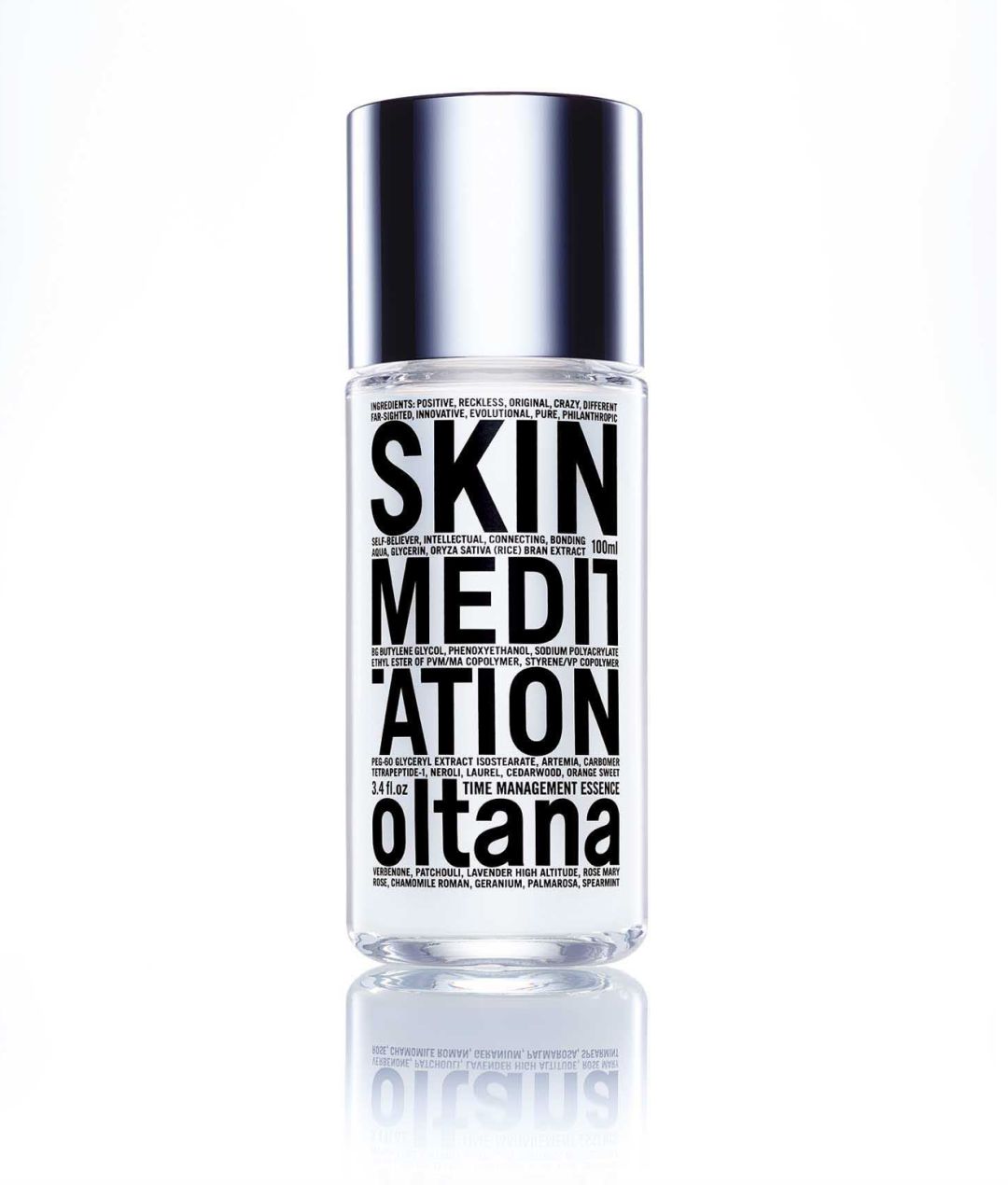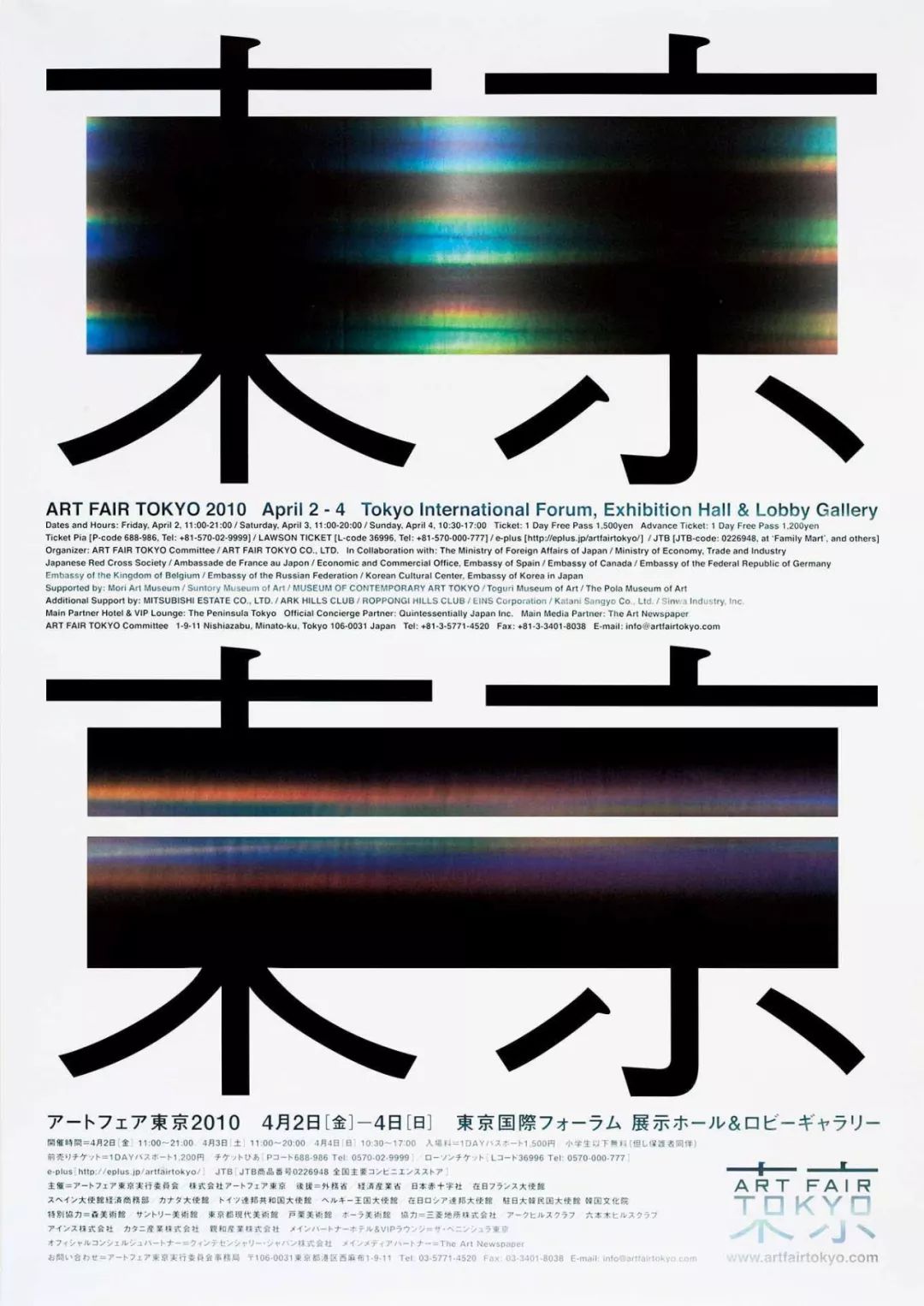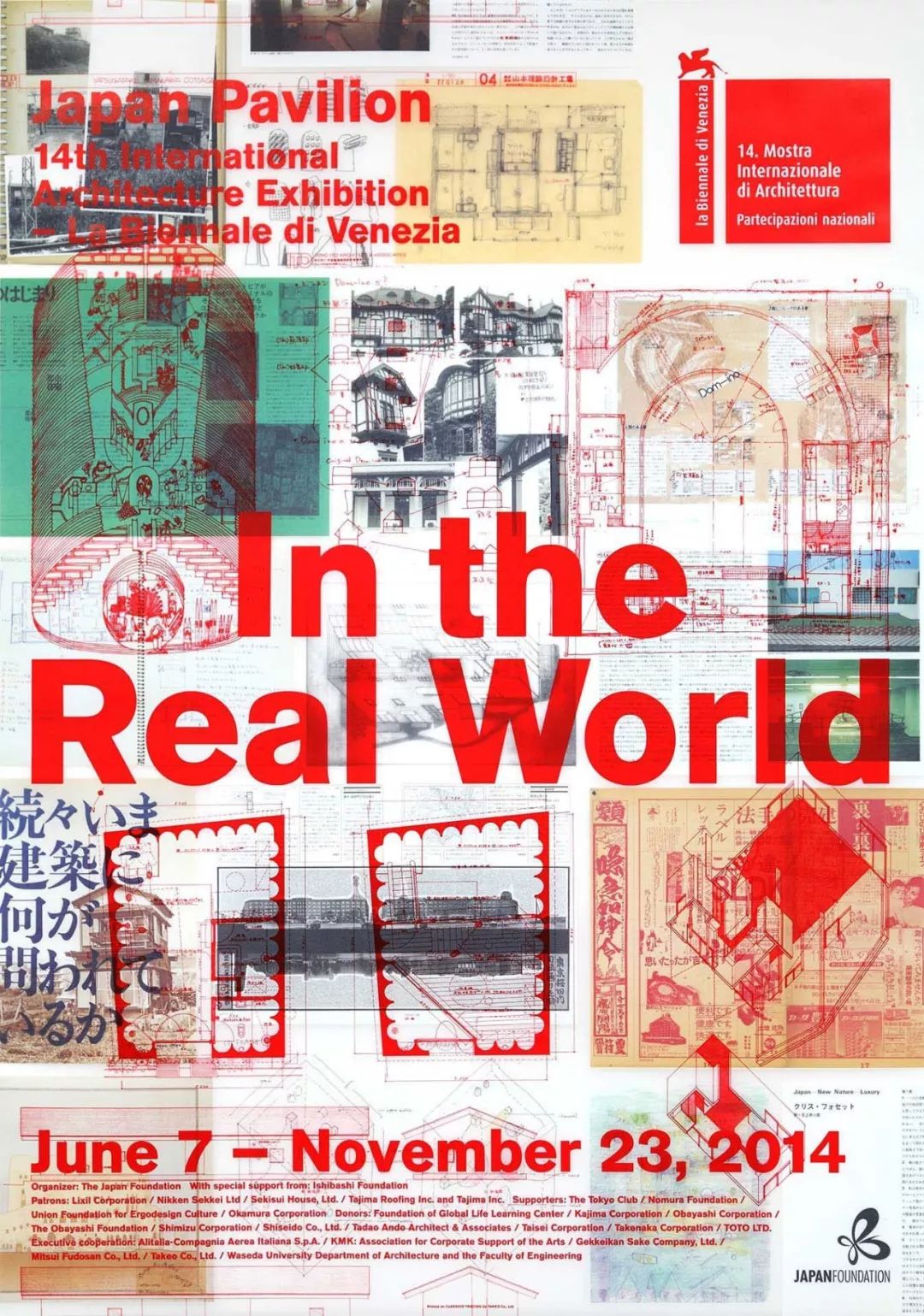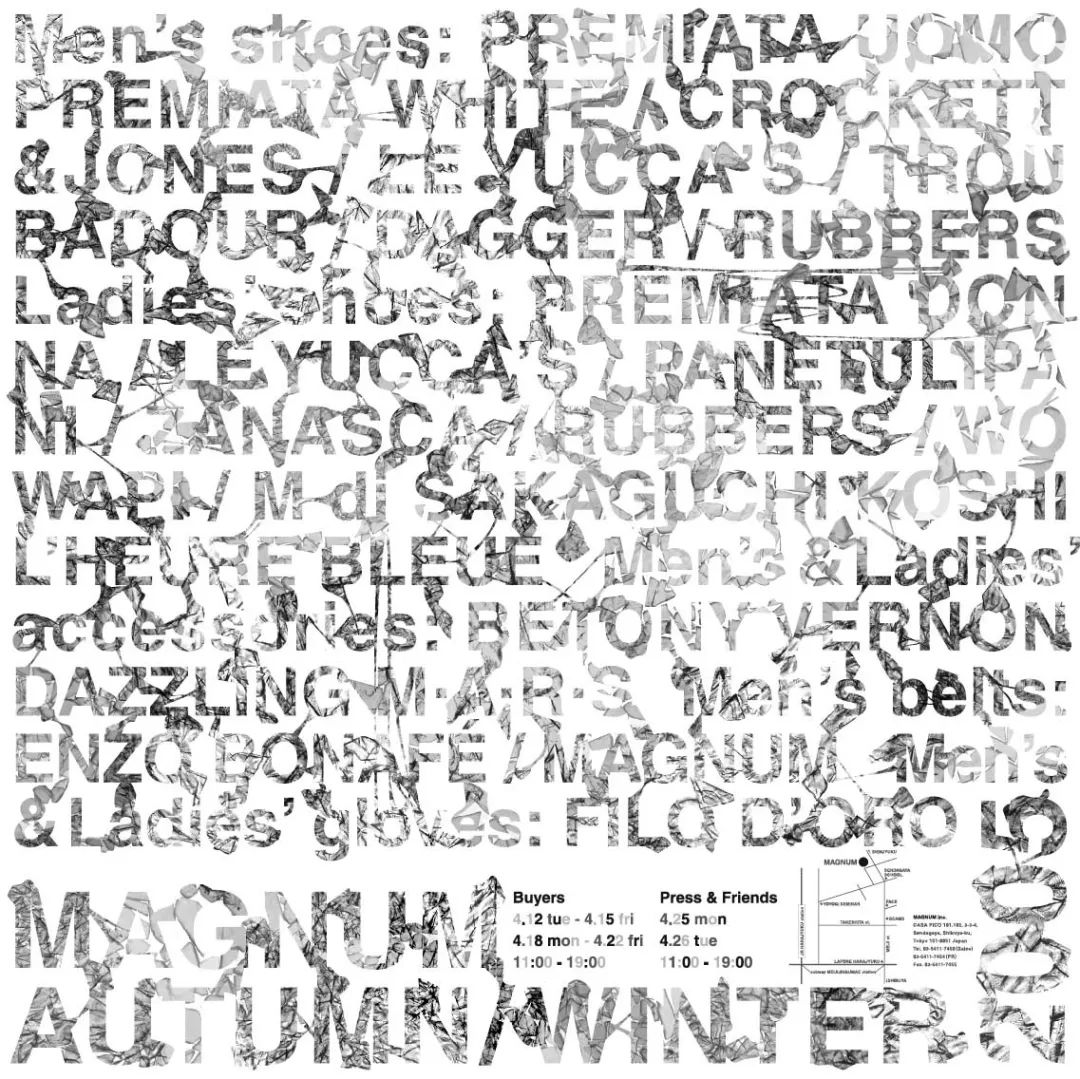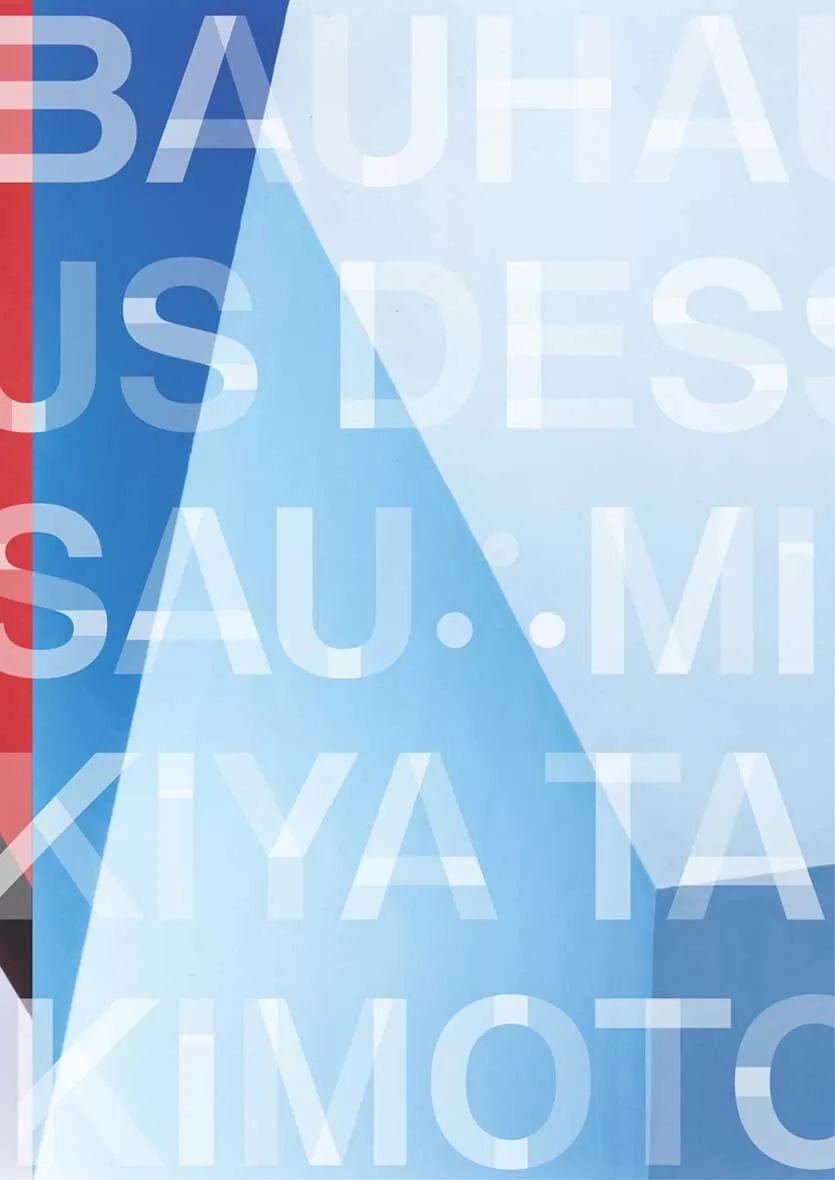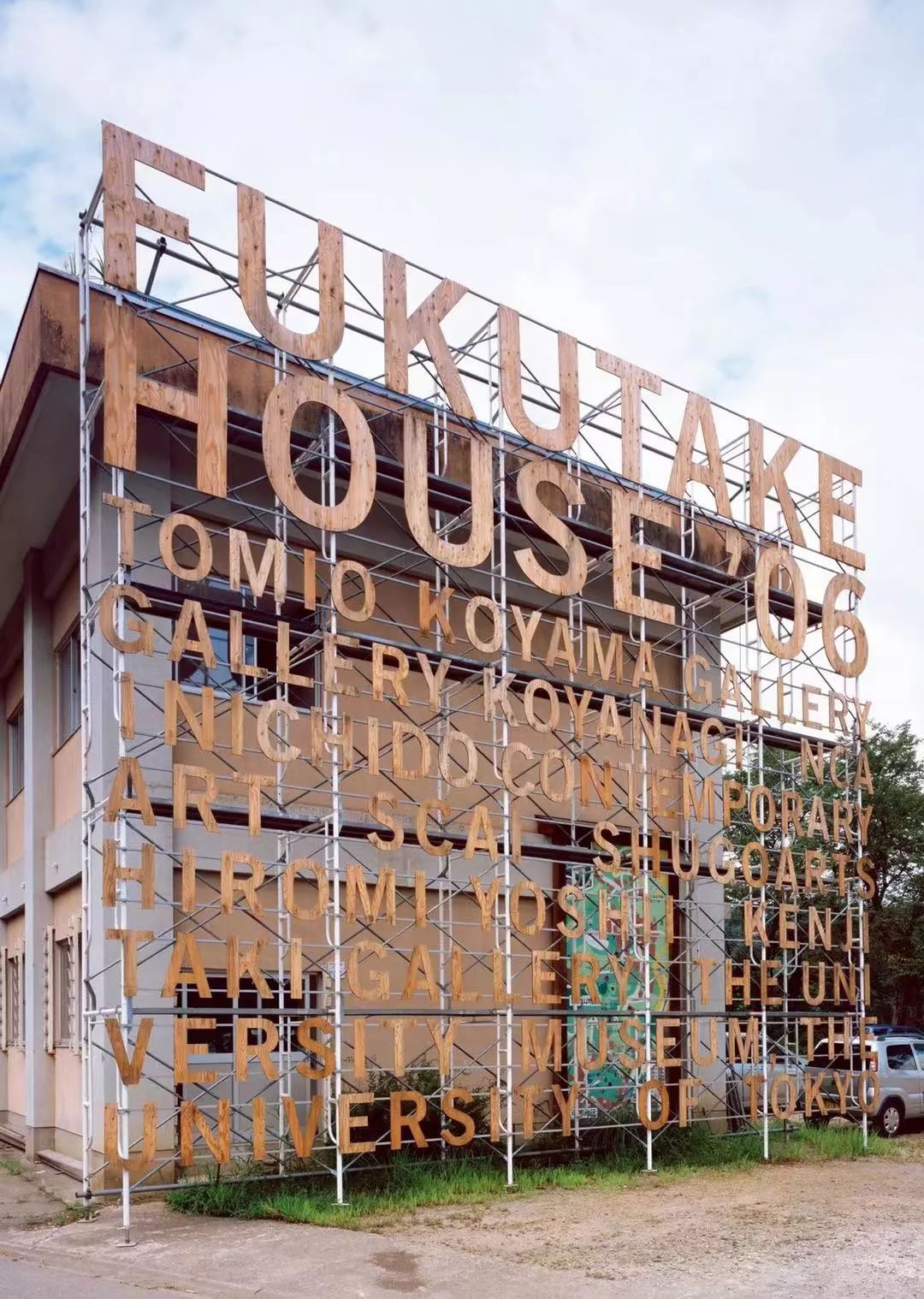
工作即人生 —— 专访日本平面设计师古平正義
长发及肩、衣衫墨色、笑声爽朗。大阪府出身的知名艺术指导、平面设计师古平正義周身弥漫了摇滚、前卫与不羁之感。可言谈起来,却格外真挚、细腻、措辞恳切。在这表里对极的背后,是JAGDA新人赏、TOKYO ADC赏、NY TDC赏等多数荣誉的褒奖。在一个嚣声过后的傍晚,我们与手执啤酒的古平先生有了一次轻松而深入的访谈,一听他设计创作与思考的前后左右。
古平正義(Masayoshi Kodaira)
1970年出生于大阪,曾在秋田宽的事务所工作,后设立FLAME。为日本艺术盛会ART FAIR TOKYO 长达十年的海报设计、担任著名的音乐杂志《滚石》日本版的艺术指导,以奈良美智展为契机,担任了水户艺术馆、森美术馆等展览会海报,获戛纳的是枝裕和导演御用摄影师龙本干也的写真集设计、与三宅一生BAOBAO系列等。
代表作
另外包括展览会的会场构成、建筑的标识设计、出版企划等他也参与其中。GLAY·INORAN等音乐家的CD封面。获得ONE SHOW 、D&AD银奖、东京ADC奖、JAGDA新人奖、SDA优秀奖、NY ADC特别奖、NY TDC奖。
Q:我们的第一个问题是:是否可以请您和我们简单的分享在事务所FLAME设立之前,您的设计修行之路。
K:我并没有上过大学,是在大阪的专门学校①读的夜间课程。因为很早以前,日本的专门学校并没有真正意义上的设计老师,所以完全学不到东西。(我)也基本上都翘了课整天尽忙着打工了。
Q:是设计方面的打工实习吗?
K:不,不是啦。尽是在瞎玩儿了(笑)曾有在一所大阪的普通设计公司就职过一回,可惜在那边也是未展自愿。但是在那里有ADC②年鉴、JAGDA③年鉴等资料。看了以后,意识到不去这些设计一线的地方不行而去了东京。基本是这样子。
Q:所以您进入秋田宽④先生事务所的时候也是在去了东京之后?
K:觉得必须去东京。就还在大阪的时候,便找了许许多多的地方,那会儿正好也是在泡沫经济之后,因而新人募集的公司相当少。实在没办法,当时在ADC,JAGDA年鉴的最后几页,刊登有设计公司的地址和电话号码,于是就一家一家的联络和拜访,其中之一,就是秋田先生的事务所。也正巧,事务所人手有所不足,因而之后被叫去(工作),算是被捡进去了。后来,在秋田先生事务所工作了四年,并又做了三、四年的自由设计师,再独立开设了自己的事务所。独立后开始搬家,事务所的室内设计也都用心的制作、邀请了片山正通⑤先生帮忙进行了室内设计,那大约是在2001年的时候了。
Q:提到 FLAME,自然使人想到的便是「ART FAIR 东京」「Laforet」「GLAY」等艺术内容设计的名作、这些案件选择的背后,能够深深感受到您对艺术类项目的偏爱。请问您是如何看待艺术与设计的关系?
K:其实刚刚在讲座内也稍有提到,像是艺术和设计的区别正在逐渐的消融。嗯…这样说也许略有偏颇,现在有许多艺术家都会在设计领域有所尝试、设计师的工作由艺术家来担当的情况感觉很多。所以,相反的,我觉得设计师去尝试艺术也应该有所增加,也应该会越来越多吧。还有或许有点儿不礼貌的来说,就是设计师的工作,比方说 Typography。一般艺术家不会做 Typography 的吧,所以有时候,艺术家进入设计领域时会搞出些古怪的设计。因为他们并不是专业的设计师。因此,艺术家仅是视觉表现的话倒也还好,如果有 Typography 之类要素的话,常常有艺术家做出来的奇怪的设计。而相反,我觉得因为不是艺术家而不能做艺术的限制要素其实并不多的吧。(笑)
Q:确实,艺术是一个相对可自由表现的领域和空间。
K:是的。所以当然并不需要将两者对立,同时,将它们(艺术与设计)的区别更加消融我觉得将会变得更好。
Q:请您和我们分享名作「ART FAIR 东京」系列的设计经纬。
K:在最初的时候,在今天提及并展示的这个 ART FAIR 海报作品之前,我仅仅是接到了设计 ART FAIR LOGO 的委托。
Q:所以,是以LOGO设计为始出发的。
K:对。在前一年先只被委托了 LOGO 的设计,以之出发,设计了 LOGO 和最初的海报。(在草稿纸上手绘出最初的海报设计草图)最初的这张海报。和现在有所不同,2005年那个时候 ART FAIR 并不像现今这么知名。所以,有了这张带有说明性的海报。说清;“ART FAIR 并不是展览会而是购买艺术品的地方。”而这个设计倒是反响很不错。我却也没有打算就仅是第一次在这边(海报中央区域)醒目的放置了 ART FILE 的 LOGO,但 ART FAIR 方面觉得就按照这“LOGO 醒目”的方向推进系列设计很好,所以至今都保持这样的设计形式。期间大约连续设计了三年以后,约第四第五年我其实曾对设计修改过。一般这样的海报把 LOGO 放的如此之大是不多的吧。所以,在设计担当时我觉得也差不多该做一些变化,在这里(LOGO 的中央空间)放一些艺术家的作品之类的改变,但果然还是被说“LOGO 是主体”,虽然 LOGO 是主体但也不可以就那样直接放着用而提出了修改别案,然后呢,因为之前的设计获得了 ADC 的设计奖,而且,比起我有时候客户更正确…(笑)。其实,有每次都提出不同的更新设计提案(再开始于草图上的绘画)像是这边放这个,再把 LOGO 移到那边,一直是“更新、要更新”的主张,但是,客户每次总还是选用基于原来样式的设计。但,是很有趣的工作。
Q:在媒体与设计媒介发展变化日趋迅速的当下,您如何看待「海报」以及其今后的发展与可能性。
K:海报的话,果然,也就像刚才讲座中略有提到的。海报将渐渐失去作为一般告知媒介的位置吧,特别中国也是如此,伴随着电子媒介越发的普及,终将会变成那样的。所以,海报今后很快也可能会成为一种艺术的媒介吧。(笑)
Q:原来如此,所以在现今,古平先生就已渐渐开始在海报上做一些带有艺术性的设计和尝试了。
K:嗯,怎么说呢。即使这样,如果城市里全都是动态电子屏幕,也会变得有些不舒服吧。
Q:全部都是动态看多了却也容易晕眩(笑)
K:(笑)所以,今后真的会变成怎么样,稍微现在还略有不知。作为商业的媒介,绝对是以智能手机、大型的电子屏为主流。以往的商业的媒介并不只有像我们做的这种类型的海报,比方说日本还有专门贴在电车里的海报。我觉得那种海报和我们所设计制作的海报基本是不同的。像这种传统的媒介虽然绝对会有变化,但是如果真的全部都变成现在的电子的媒介,当然觉得也不是不可能,但也觉得真变成那样了会不舒服,对人的身体也不是很好的感觉(笑)。嗯,或许还会诞生某些更加不一样的东西。难说。虽然现在有些难预想。怎么说,也许话题会略微的有些扯远。现在用手机都可以随时随地的听音乐吧。但是,如果全部都是以这样的方式来听音乐的话,就不好玩儿了。所以现在也有人购买黑胶来听,觉得如果全部转化为数据化,人就会变成像机器人那样的存在,不太……
Q: 缺少了多样性的世界果然就缺少了很多有趣的部分。
K:对!果然大家看各种各样的不同的(手指海报),那样不更有趣不是吗?
Q:所以,将来也有可能是传统媒体和电子媒体保持多样性的共存下去……
K:目前会变成什么样还不知道,但是一般想来,比起画面中许多元素动来动去,贴有漂亮海报的空间会更加舒服吧(笑)将来到底会变成什么样呢,现在也拭目以待。
比起日本,我觉得中国设计更有可能性。
Q:您对中国是否有了解,对中国的设计是否有了解并怎么看中国的设计。今年担当GDC评委的色部義昭先生有对中国的海报以及书籍设计相当的肯定,但是也有表示品牌设计和包装还颇有上升空间,您是如何看的。因为曾经您也有做过 D&AD 的评委,其间也有出现过很出挑的来自中国的书籍设计作品,一样,相比品牌和包装略少。
K:是的。基本上我也这么认为。像品牌,LOGO 之类,或许色部君也是这样的观点,像是海报或者 LOGO 设计是相对比较可以做到不过于被干扰的偏个人性的项目。(其它)中国的设计作品总体来看,大家普遍都有“带着工作感完成”的感觉。
Q:是指专业性高的意思吗?
K:在日本,我们会用:“代理店感”⑥来形容。(笑)怎么说呢,商业感很强。日本以前也是,当然现在这种类型也依旧很多,但是,嗯,日本应该也和中国一样。比起日本,我觉得中国设计更有可能性。因此,向那类大型的设计项目再多多的挑战会更好。目前,在那些大型的项目中很有“代理店感”的感觉。即使不是海报或者是书,比如说小的店铺的项目之类,好的作品还是有很多的,项目越大就越感觉太呈现出商业感。就会冲淡现在中国设计师们非常努力并去构建的好的设计感。
Q:现在中国的设计师大家,其实常常会遇见这类的问题。比方说客户和项目有相当的规模,因此支付高额项目设计酬金的客户自然会按照切实实现其脑内所想的视角去影响设计。
K:哈哈哈!日本当然也一样的。关于这点就要看如何游刃的处理了。
Q:嗯,果然古平先生您是否有哪些独门技巧和秘方呢?
K:有是有。关于那点,要看如何的良质沟通啊,巧妙隐藏啊,以及吵架啊。
Q:吵架?
K:对,争吵也是沟通的一种形式。这个日本也一样的。电通也有这样的情况。或许,稍微更早些时候的日本更好,现在日本也…其实不仅日本,这应该是世界范围内都有的情况。所以,不是设计展或者设计比赛获奖的作品内容都易是那些不很大的项目吗。(笑)
不是因为收了钱而听话的去做设计,而是必须坚信经大家跬步至今奋发于明的努力积累去涤净社会。不要输给钱。
Q:最后一问。您认为:「设计为何」?
K:嗯…就是人生吧!(笑)更普通些来说的话,就是:工作。工作即人生。音乐家就是音乐,嘛,没办法得做啊…
Q:哈哈,没办法得做…所以如您刚刚讲座中所提,赶快需要AI的技术来协力设计。
K:哈哈,是的是的。设计有许多意思,工作,社会。比方音乐家就以音乐和社会关联,我们设计师就与以设计与社会发生关联,所以,与在SNS上批判之类的相比,像现在所提到的,不是因为收了钱而听话的去做设计,而是必须坚信经大家跬步至今奋发于明的努力积累去涤净社会。不要输给钱。哈哈哈。这个很难,而且,如果不是大家一起的话,很难的。
Q:确实,个人的力量总见渺小。
K:对的。像我这样总是会吵架,工作也就渐渐的规模越变越小。有点困扰。(笑)我们继续刚才的话题,以前在日本设计师大家都和客户吵架的。经常吵。我工作的时候还摔客户电话呢:“那种要求我做不了!”…叭的。也就是那时,像浅叶先生的时期,设计一下子变得很不错。现在,刚刚提到的品牌的话题,日本也有这个问题,因为是收取设计费用的就乖乖的听客户的话,作为一种文化情状。实际上是容易变弱的。